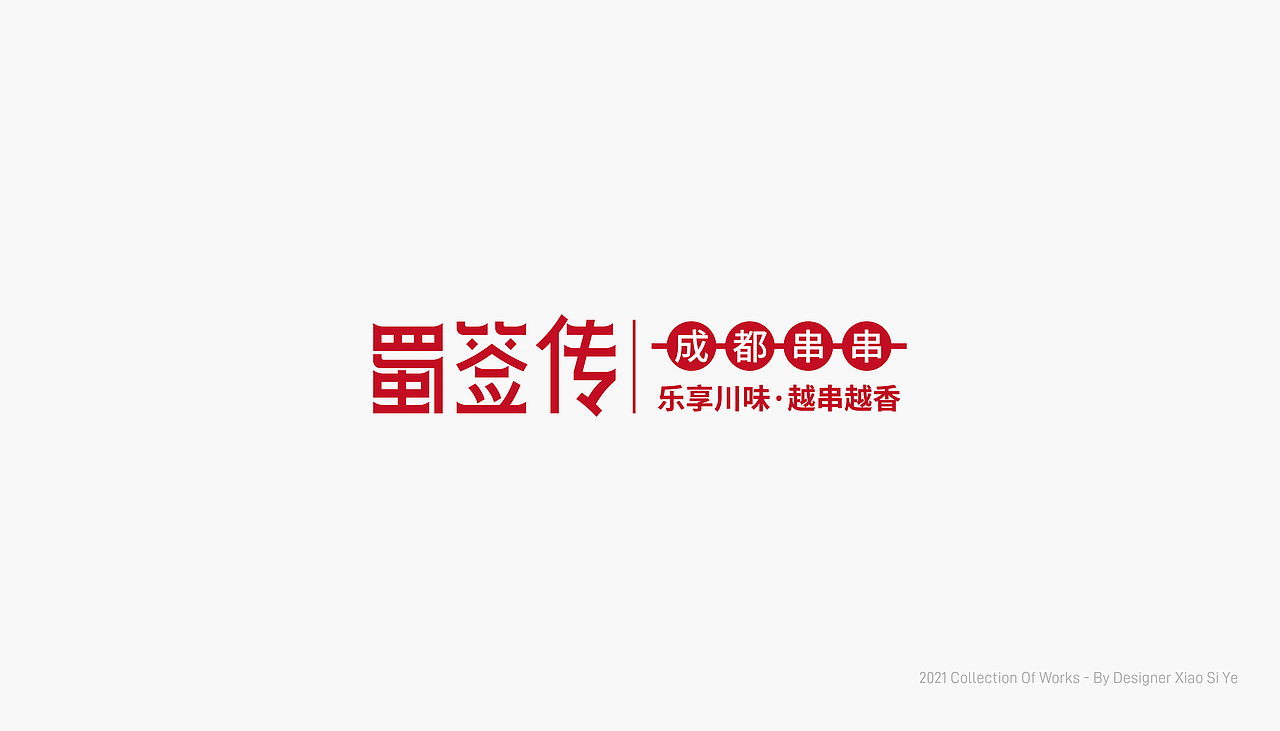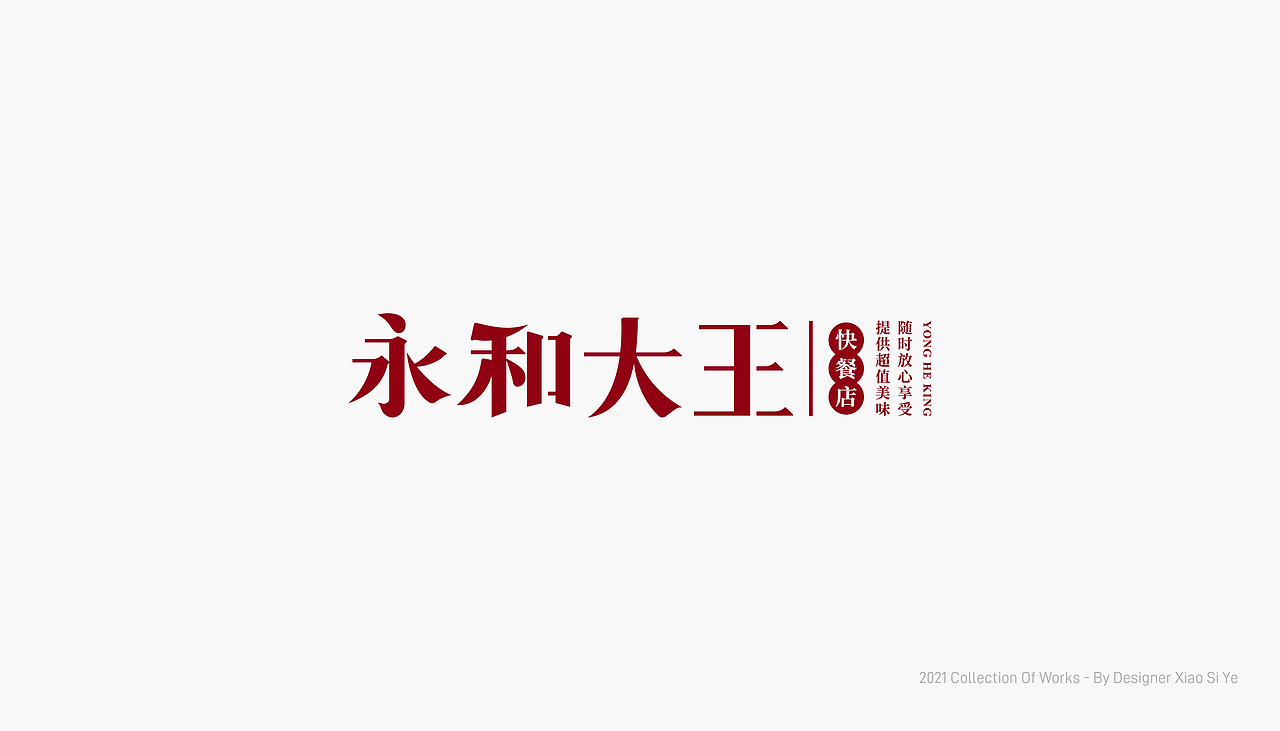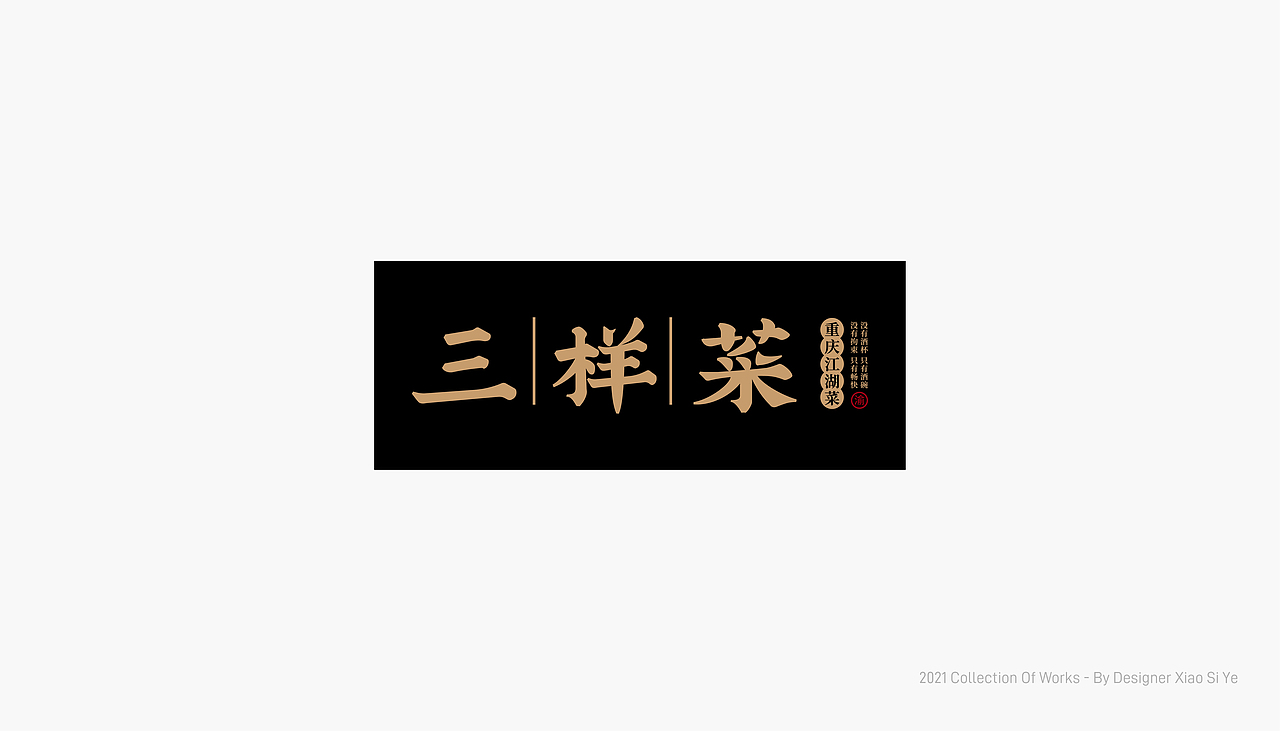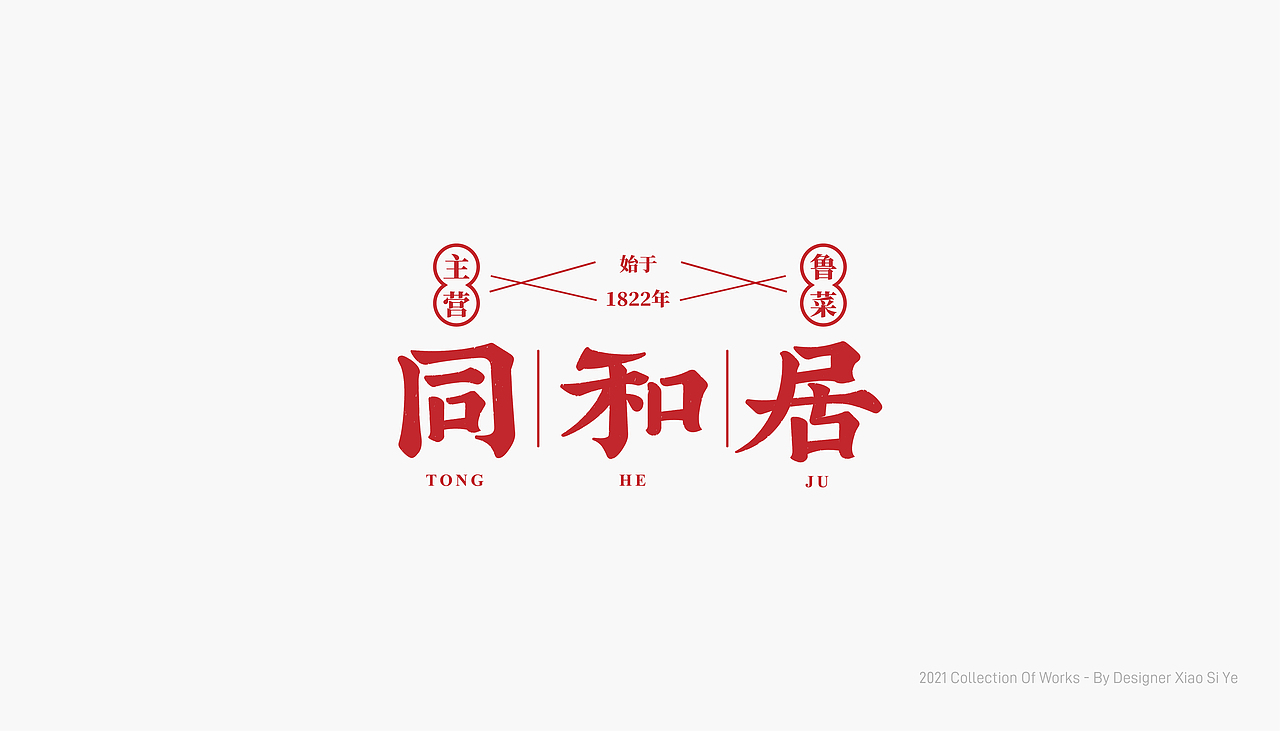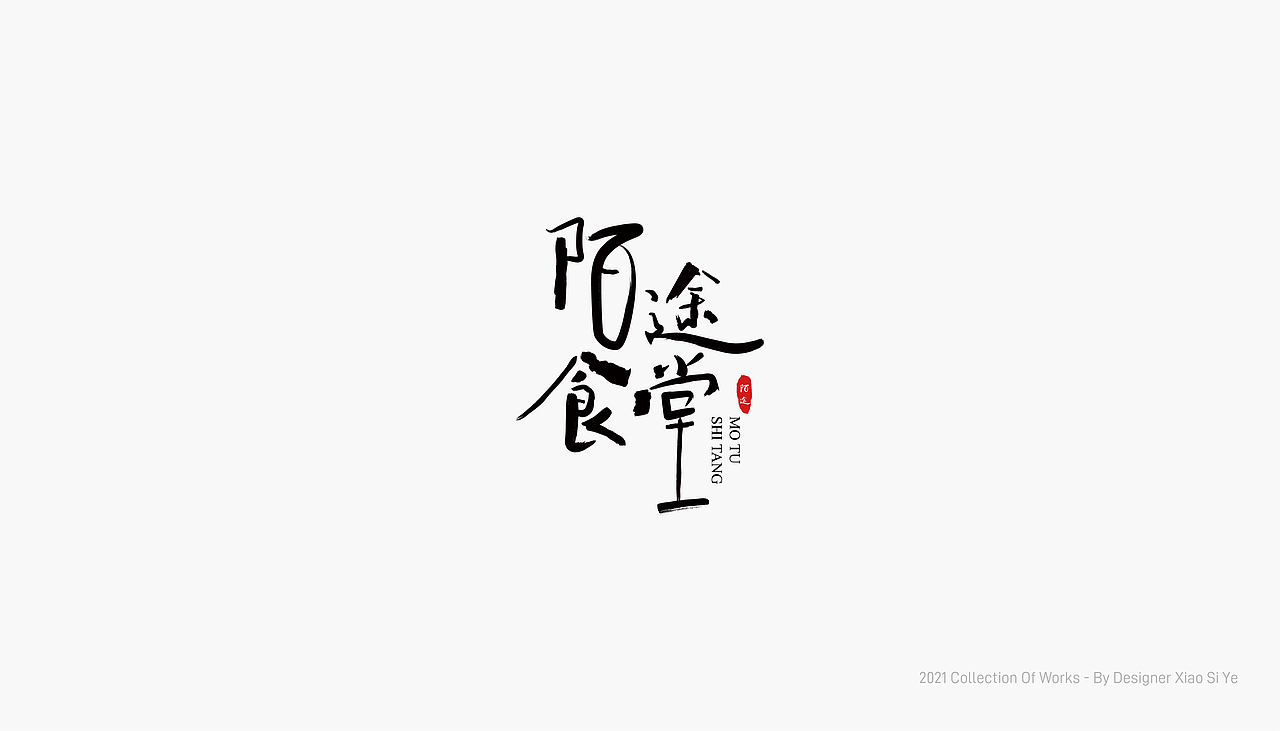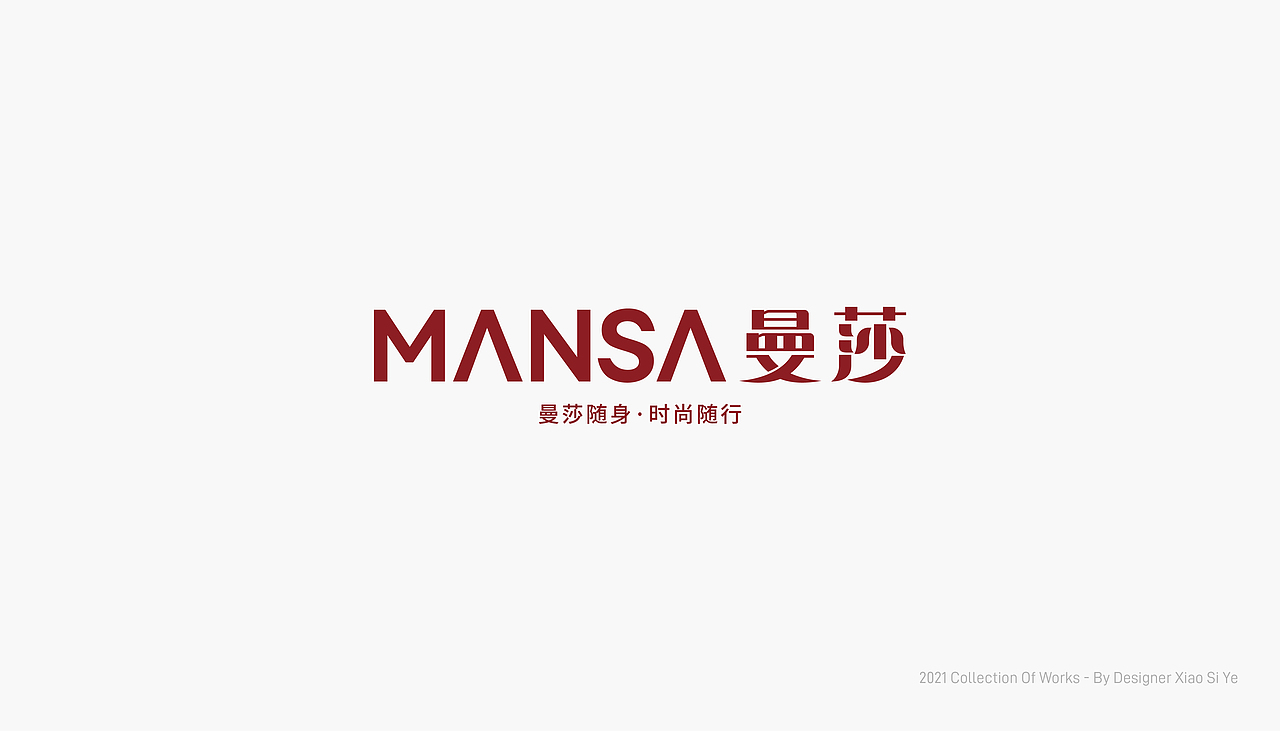
字体LOGO合集(二)
字体LOGO在标志领域独具优势,
因其识别高、传播快、好注册,
越来越成为客户的首选。
一款易被客户认可的字体LOGO,
不仅前期需要有好的概念、策略做铺垫,
在字体设计上,更要有差异化的亮点,
这样,才能被人一眼记住,过目不忘。
有时候,静下心来去做设计,
灵感会在不经意间出现。
慢是这个时代的奢侈品,
热爱是给自己最好的礼物,
兼而有之,幸运又幸福!
近期又整理了一波字体LOGO的小合集,
互相交流、共勉,一起成长。